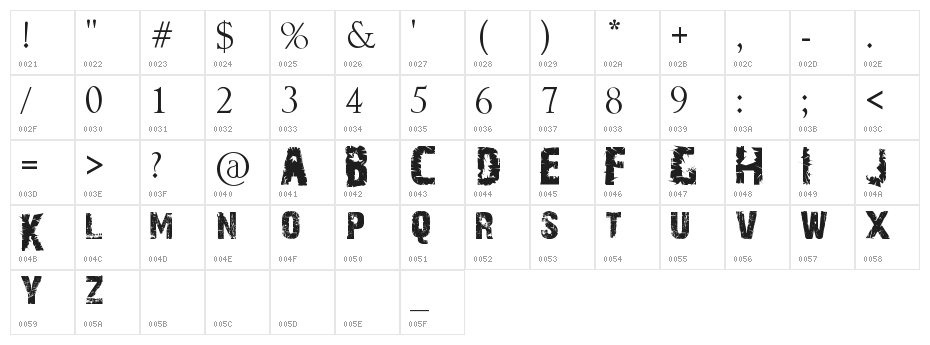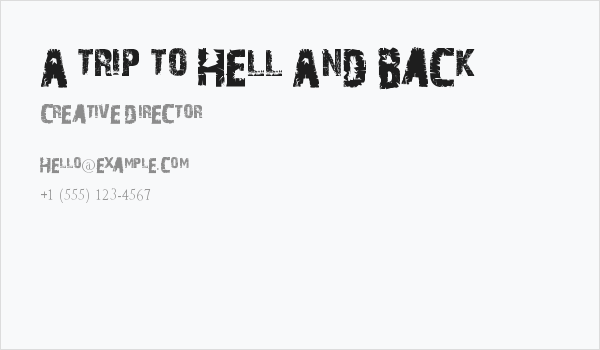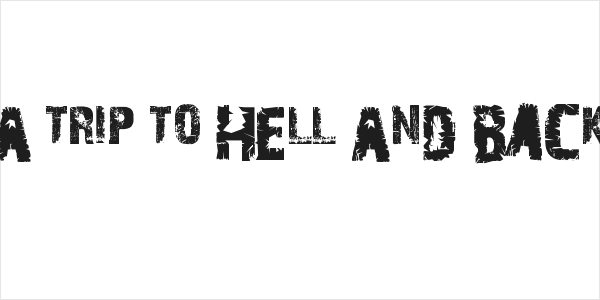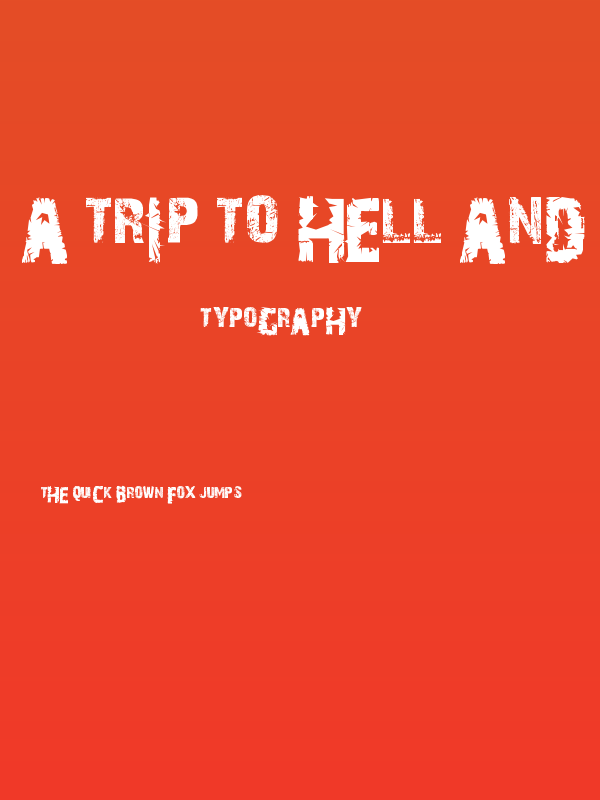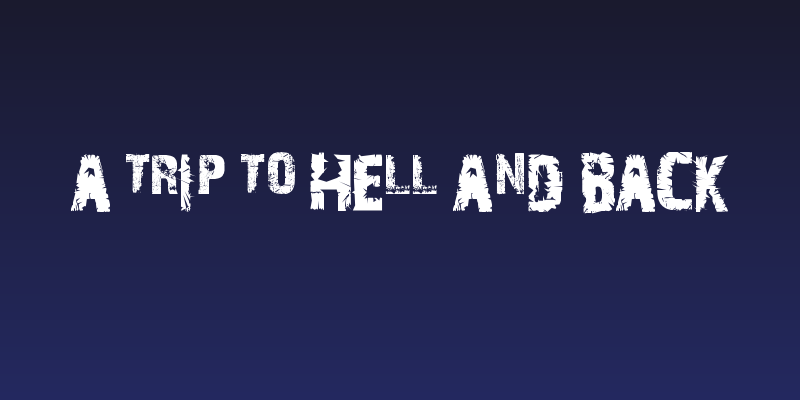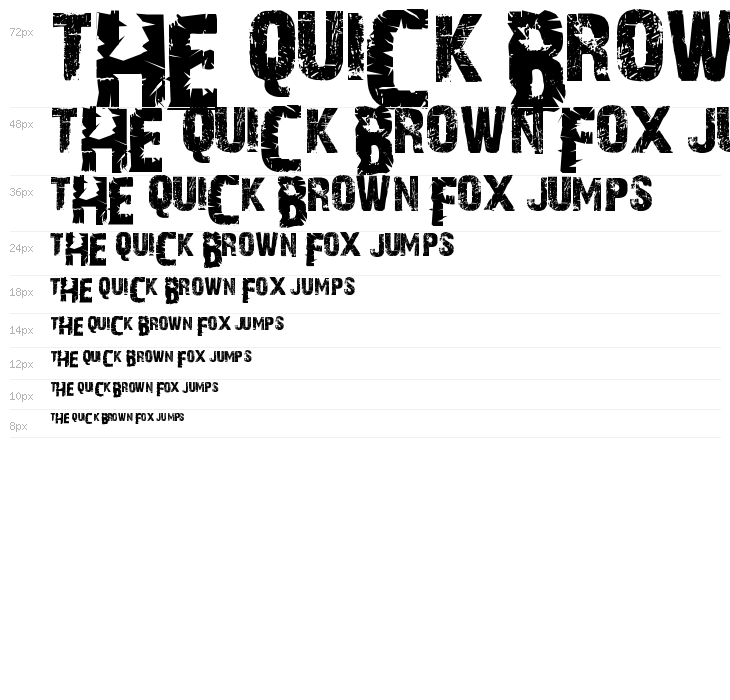
A Trip To Hell And Back Font
✎ Distorted Eroded
| Vorgeschlagene Projekte | Album covers, poster designs, branding for edgy or alternative products, and event promotions. |